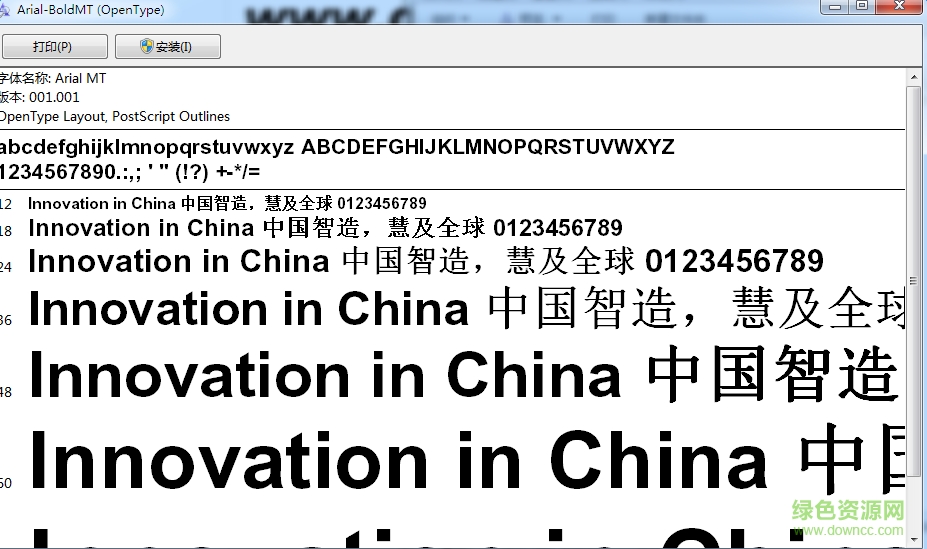
arial boldmt字體都是一款非常實(shí)用的電腦字體,這款字體看上去非常的顯眼,可以給文字編輯工作使用,高端的氣質(zhì),更加適合傳達(dá)文字表達(dá)的意思,感興趣的朋友歡迎下載使用!
arial boldmt是一款非常有特色的英文電腦字體,字形優(yōu)美,可以用于文字排版、美工設(shè)計(jì)、廣告設(shè)計(jì)、海報(bào)設(shè)計(jì)等方面!